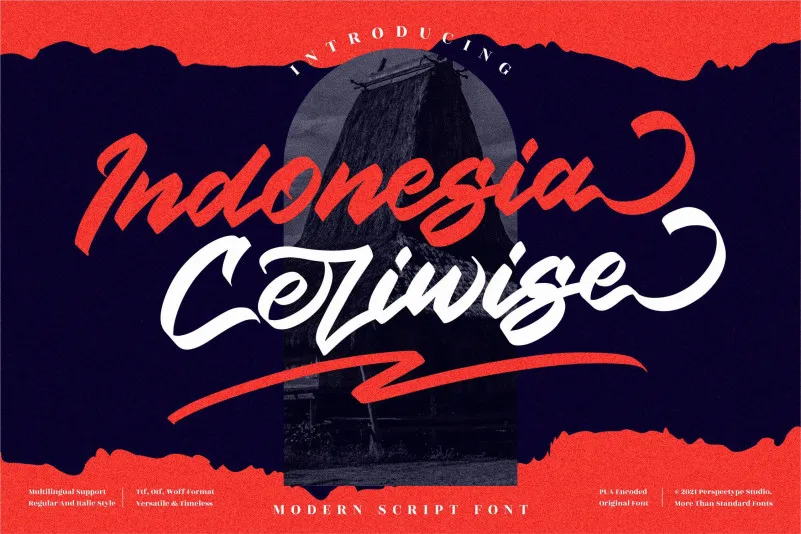
A Indonesia Ceriwise Font é uma elegante escolha para quem busca um estilo script com atemporalidade e personalidade. Embora seja classificada como uma fonte de estilo script, ela traz um toque de escrita realista que pode tornar seus projetos visuais mais interessantes. Esta fonte é ideal para headlines e logotipos onde você quer transmitir uma mensagem forte e confiante, sem abrir mão da sensação nostálgica característica dessa família de letras. Indonesia Ceriwise oferece um equilíbrio perfeito entre modernidade e charme vintage. Suas linhas suaves e o estilo retrô de sua escrita garantem que a fonte não soe antiquada, ao mesmo tempo em que contribui significativamente para a criação de uma atmosfera nostálgica inerente à forma manual da letra. Perfeito tanto para criar designs atuais quanto para dar um toque de nostalgia clara em projetos mais tradicionais, é uma opção ótima para designers buscando uma fonte que se adapta a diversos estilos sem comprometer seu poder impactante e elegância.